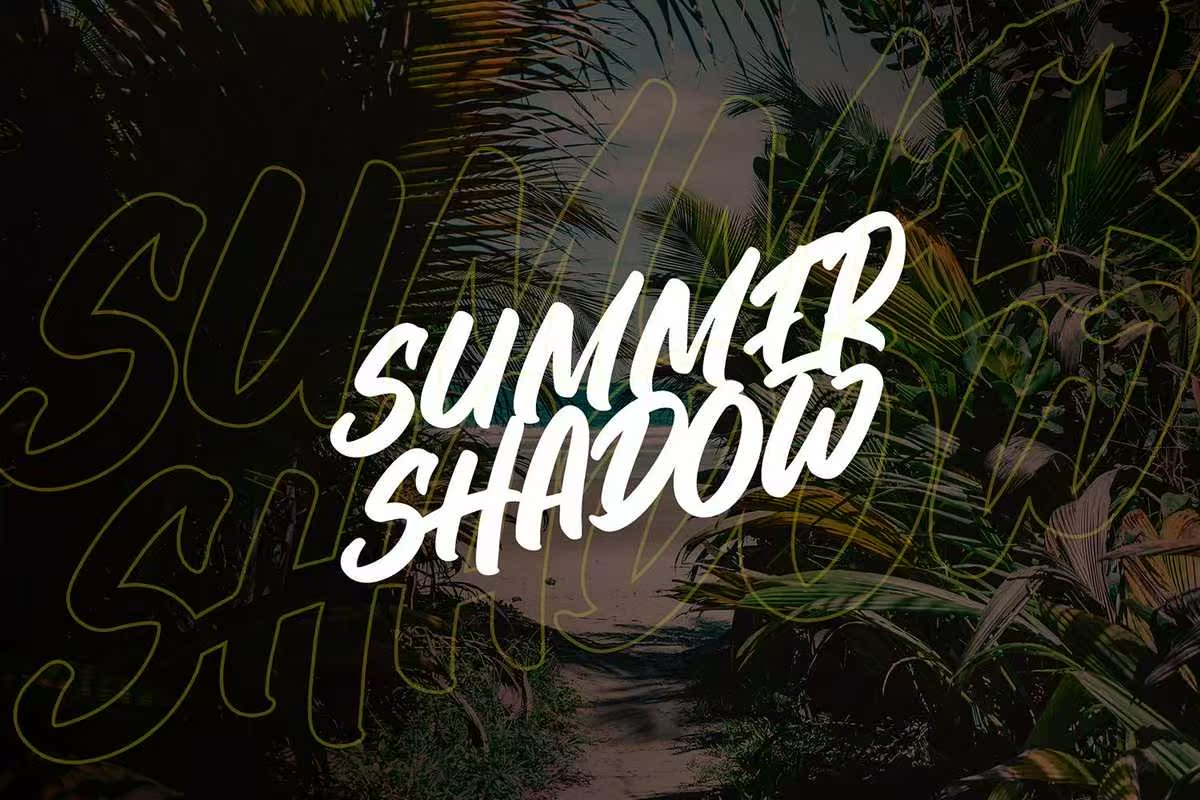
HothamisAfontmadeInnatural和WritingStyle。使用Abold Style,Hotham看起来更具吸引力,会让您的所有工作书更令人印象深刻。适用于品牌、海报、徽标、打印报价、邀请函、图像叠加、问候卡、产品包装、文本标题、问候卡、书皮、绘画设计风格,或者任何需要自然和个性化触感的设计&任何你想象得到的东西!HothamisAfontmadeInnatural和WritingStyle。使用Abold Style,Hotham看起来更具吸引力,会让您的所有工作书更令人印象深刻。适用于品牌、海报、徽标、打印报价、邀请函、图像叠加、问候卡、产品包装、文本标题、问候卡、书皮、绘画设计风格,或者任何需要自然和个性化触感的设计&任何你想象得到的东西!